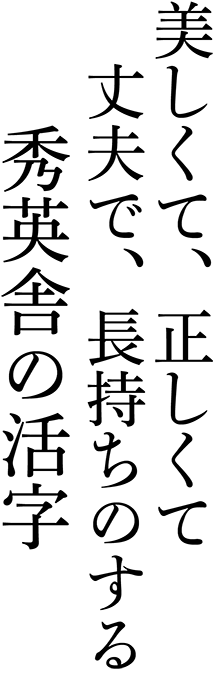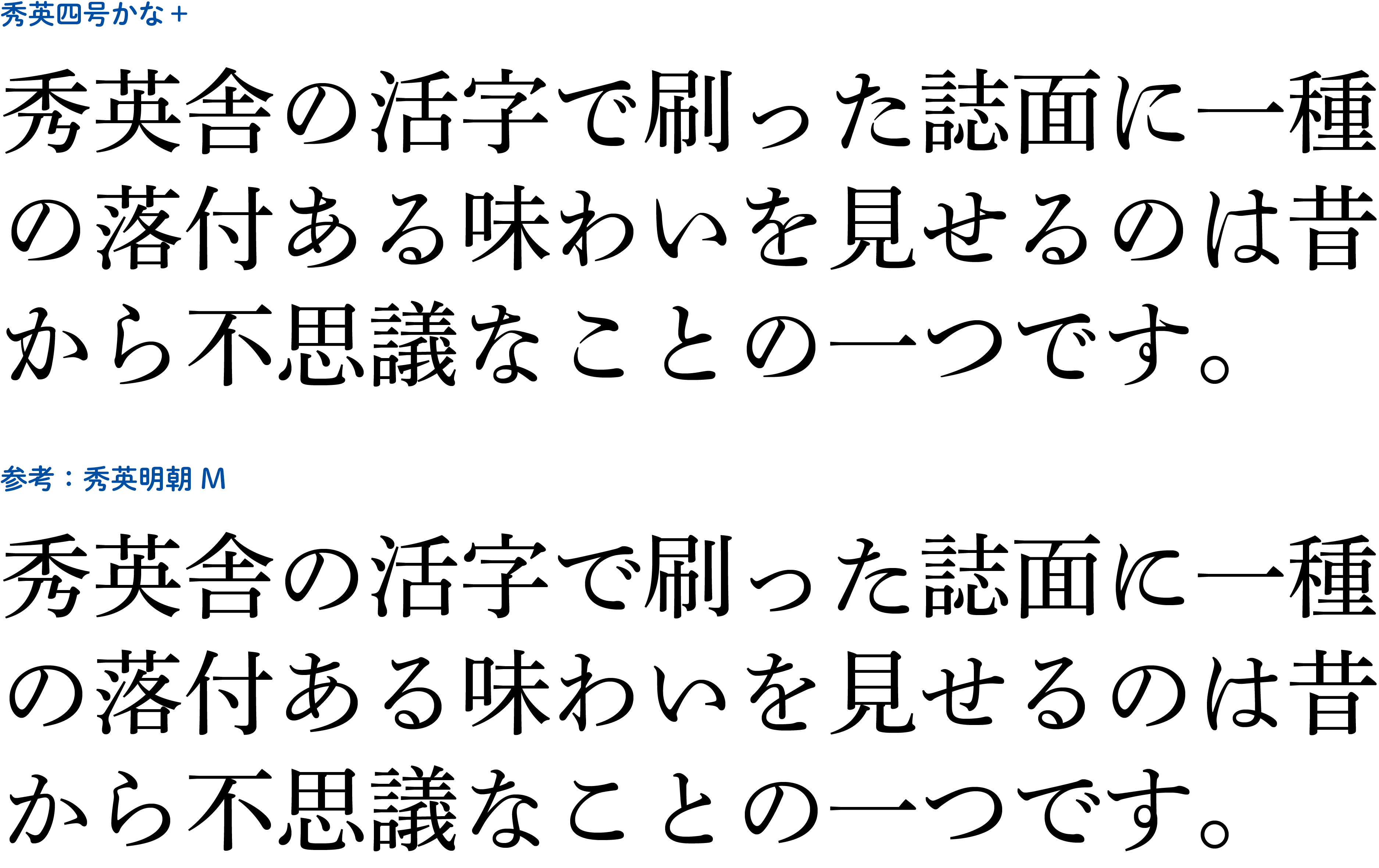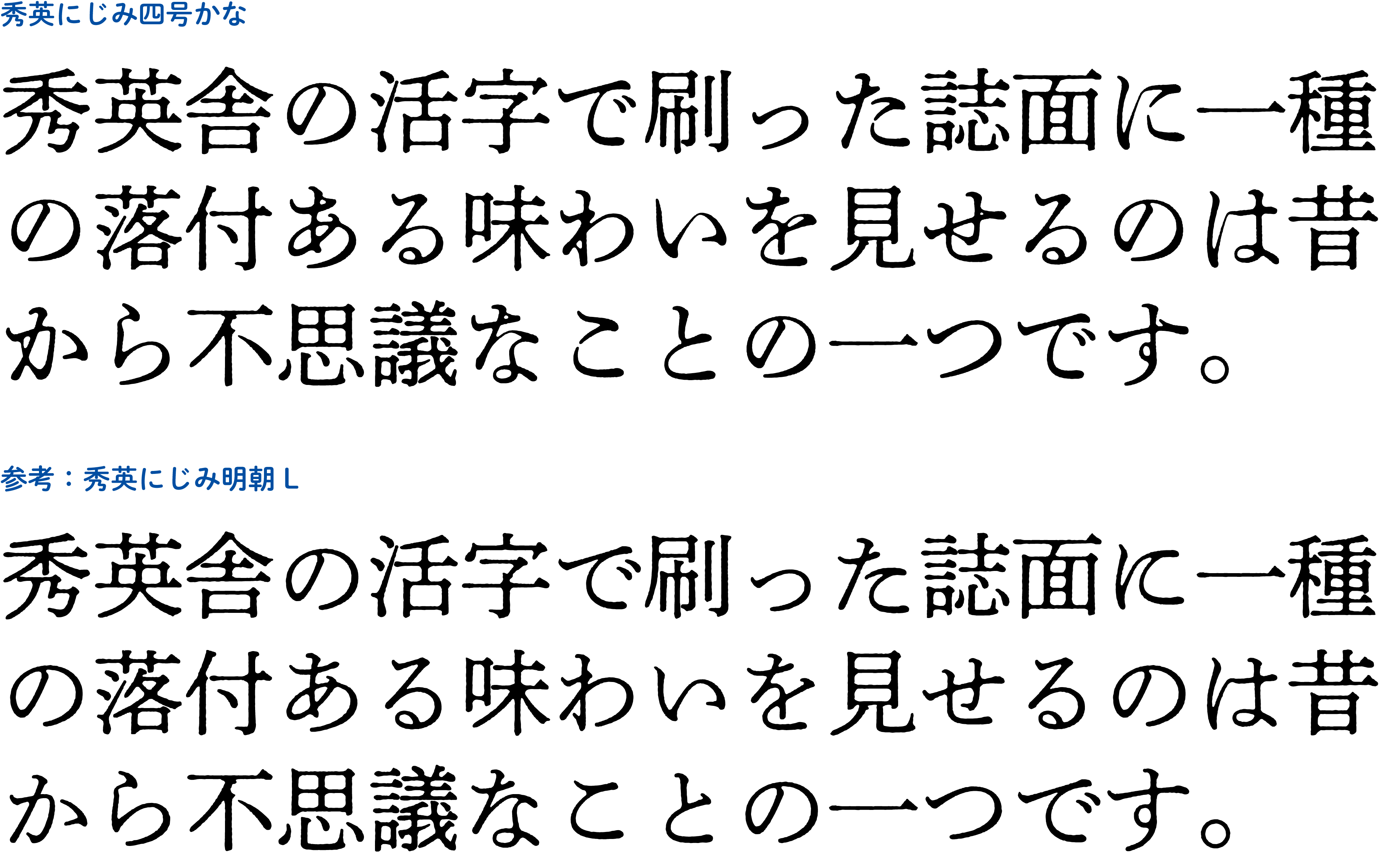
「秀英四号かな+」「秀英にじみ四号かな」を拡充し、今秋モリサワから提供
秀英四号かな
提供書体:秀英四号かな+
秀英にじみ四号かな
大日本印刷株式会社は、株式会社モリサワに2016年からライセンス提供しているオリジナル書体「秀英体」ファミリーのひとつ「秀英四号かな」シリーズについて、漢字を追加して搭載文字を拡張した「秀英四号かな+」と活版印刷の紙とインクの質感を思わせる「にじみ効果」を加えた「秀英にじみ四号かな」の2書体を追加します。モリサワは、この2書体をDTP用フォント製品として今秋に発売するほか、Webフォントサービスでも提供する予定です。
「秀英四号かな+」
現在の「秀英明朝」のルーツとなる活字「秀英四号」を復刻した仮名と、「秀英明朝 M」の漢字や記号を組み合わせた書体です。秀英体らしい端正さ、古典的で上品なデザインを持ち、本文組の適正だけでなく、タイトルや見出しでも映えるオールラウンドプレイヤーとも言えます。大きな文字サイズで使用しても、柔らかいカーブが再現され、「秀英明朝」よりもクラシックな印象を与えることができます。
秀英四号かな+ 書体見本
「秀英にじみ四号かな」
「秀英四号かな」に「にじみ効果」を持たせ、漢字と欧文に「秀英にじみ明朝L」を組み合わせた書体です。「にじみフォント」は、「秀英体」の活字で活版印刷された際の自然な“ゆらぎ”や“にじみ”を分析し、その風合いをデジタルフォント向けに再現した書体です。活版印刷では、インクの着いた活字が紙に押し付けられて印刷されるため、インクの“にじみ”や金属活字自体には無い“ゆらぎ”が自然に生じて、それが独特の風合いを生んでいます。紙とインクの質感を思わせる「にじみ効果」により、これまでのシャープで均質的なデジタルフォントでは出しにくかった、柔らかくレトロな雰囲気の味わいある表現を、各種情報端末のビューアーやWebサイト等でも実現します。
秀英にじみ四号かな 書体見本
この秋、「秀英四号かな」がパワーアップします!